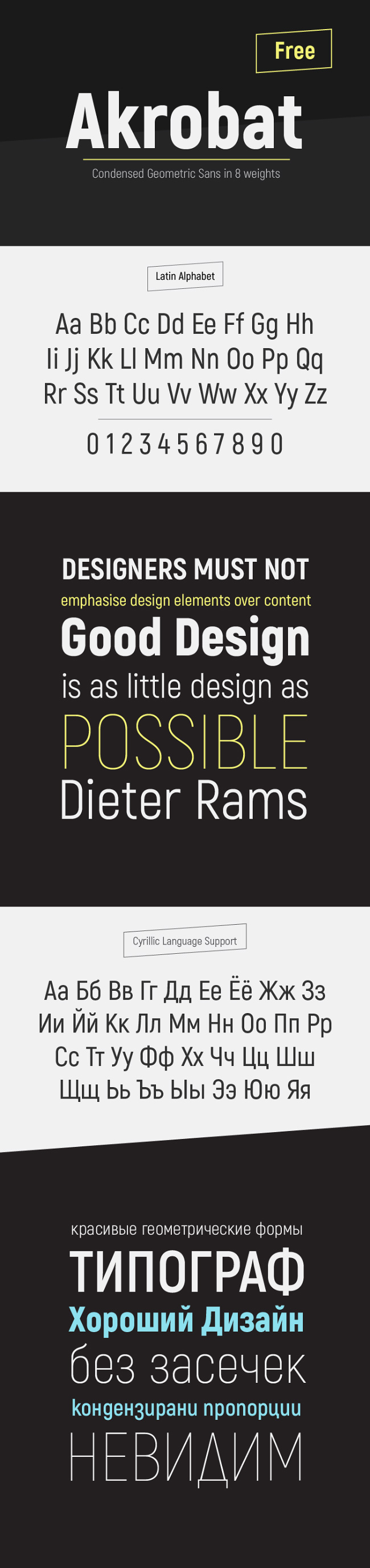
А подскажите с каким шрифтом сочетается акробат, если речь идёт о заголовке и тектсе ( акробота в блоке текста)
Анастасия Горюшова, мне кажется "жирненькие" шрифты ему подойдут,как с засечками так и без в качестве заголовков. А можно им одним обойтись меняя начертания, у него их много.